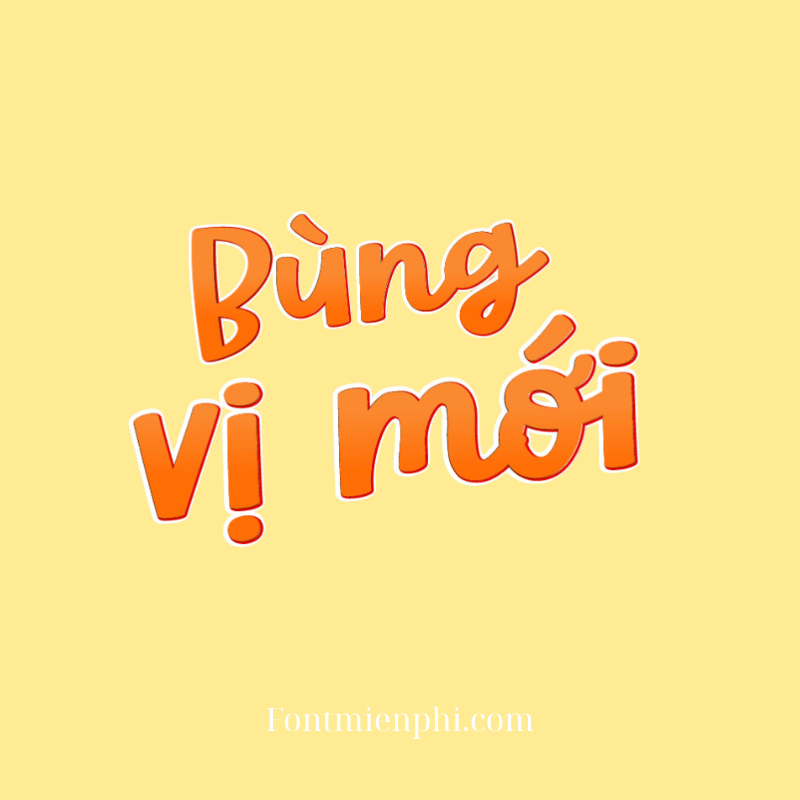
Font Việt hóa 1FTV VIP Hello Farmer , Font ẩm thực
Font Việt Hóa 1FTV VIP Hello Farmer – Font Ẩm Thực Độc Đáo
Giới Thiệu:
Font Việt hóa 1FTV VIP Hello Farmer là bộ font chữ nghệ thuật độc quyền, thiết kế dành riêng cho lĩnh vực ẩm thực, nông nghiệp và ẩm thực đồng quê. Với phong cách tươi vui, gần gũi, font chữ này mang đến cảm giác mộc mạc nhưng không kém phần sáng tạo, phù hợp cho menu nhà hàng, quán café, thực đơn món ăn hoặc các thiết kế liên quan đến nông sản, đồ handmade.
Đặc Điểm Nổi Bật:
• Hỗ trợ Tiếng Việt: Tương thích hoàn hảo với bảng mã Unicode, đảm bảo hiển thị sắc nét các dấu tiếng Việt.
• Phong Cách Độc Đáo: Nét chữ mềm mại, kết hợp họa tiết thủ công, gợi nhớ đến hương vị đồng quê và ẩm thực dân dã.
• Đa Dạng Ứng Dụng: Dùng cho thiết kế in ấn, quảng cáo, bao bì sản phẩm, poster ẩm thực hoặc nội dung digital.
Kết Luận:
1FTV VIP Hello Farmer là lựa chọn lý tưởng cho các dự án thiết kế gắn liền với ẩm thực và nông nghiệp. Với tính thẩm mỹ cao và khả năng tương thích tiếng Việt, font chữ này chắc chắn sẽ làm nổi bật thương hiệu của bạn!